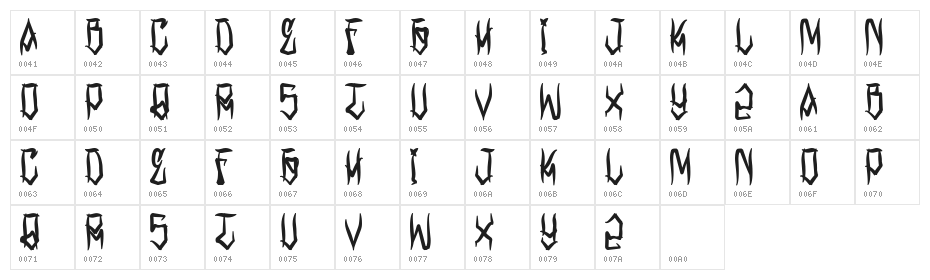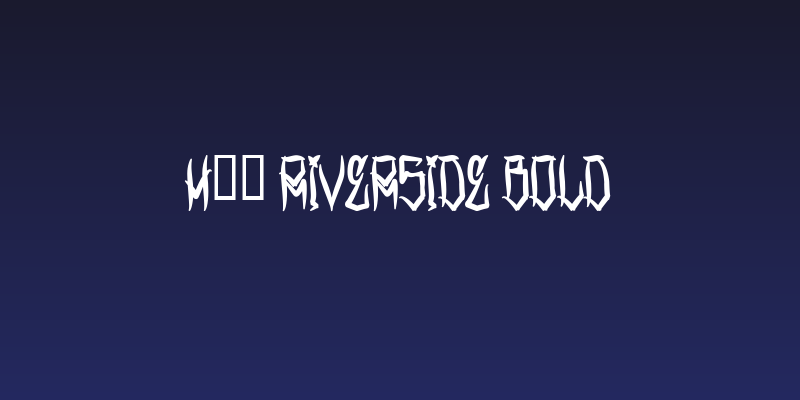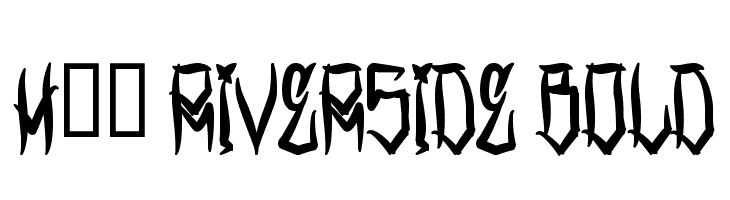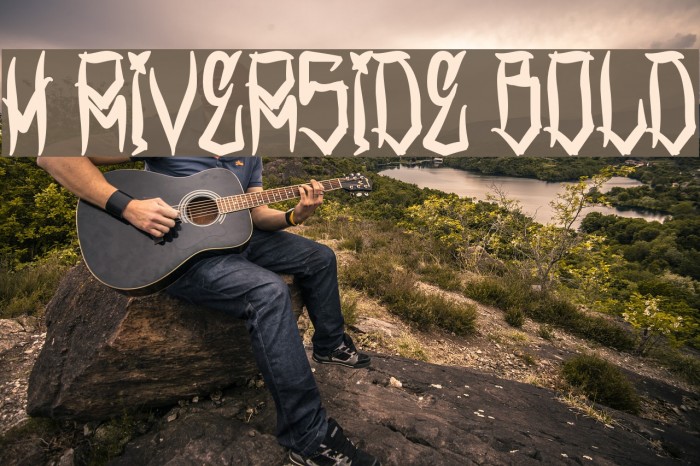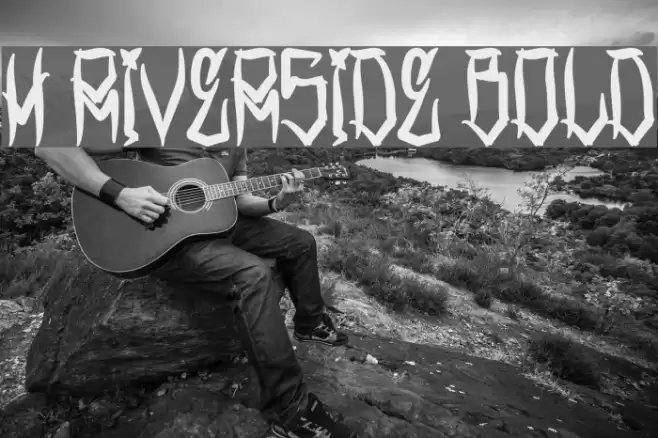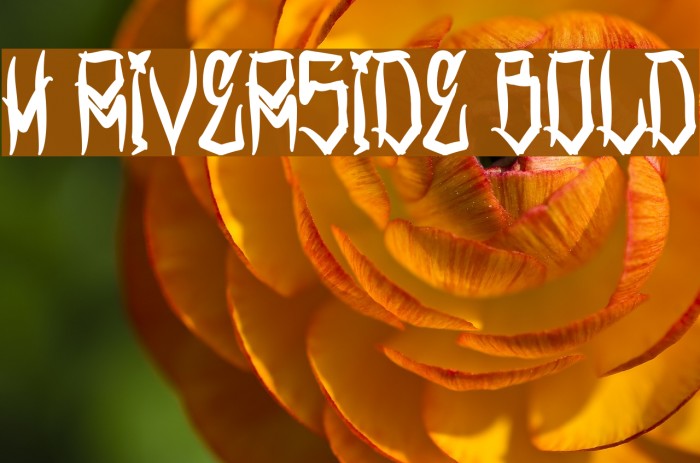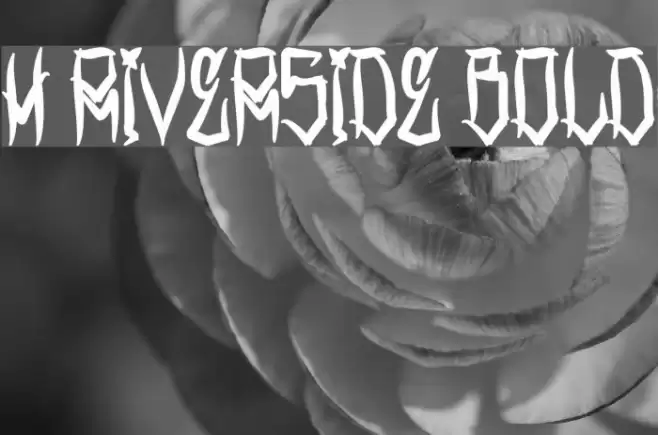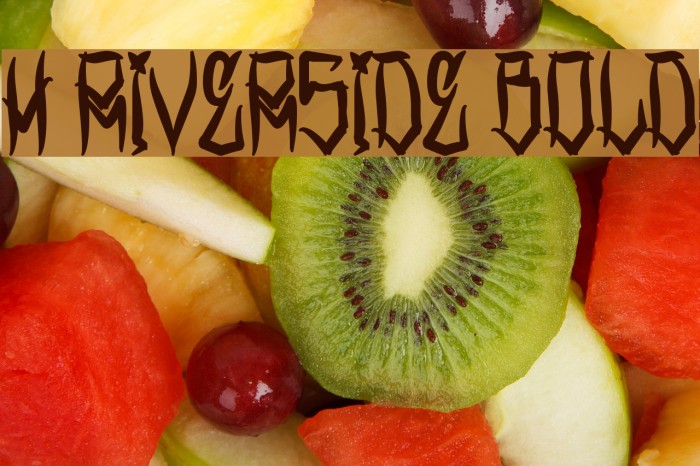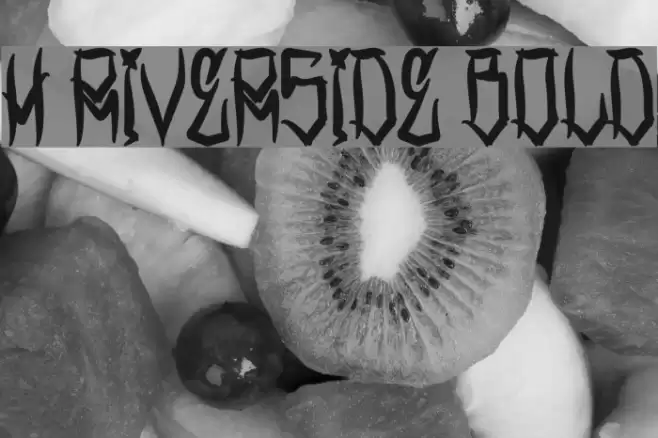
H74 Riverside Bold Font
✎ Gothic
| Style général | Gothic, Edgy, Avant-garde |
| Projets proposés | Ideal for album covers, posters, and branding that require a strong, rebellious aesthetic. |